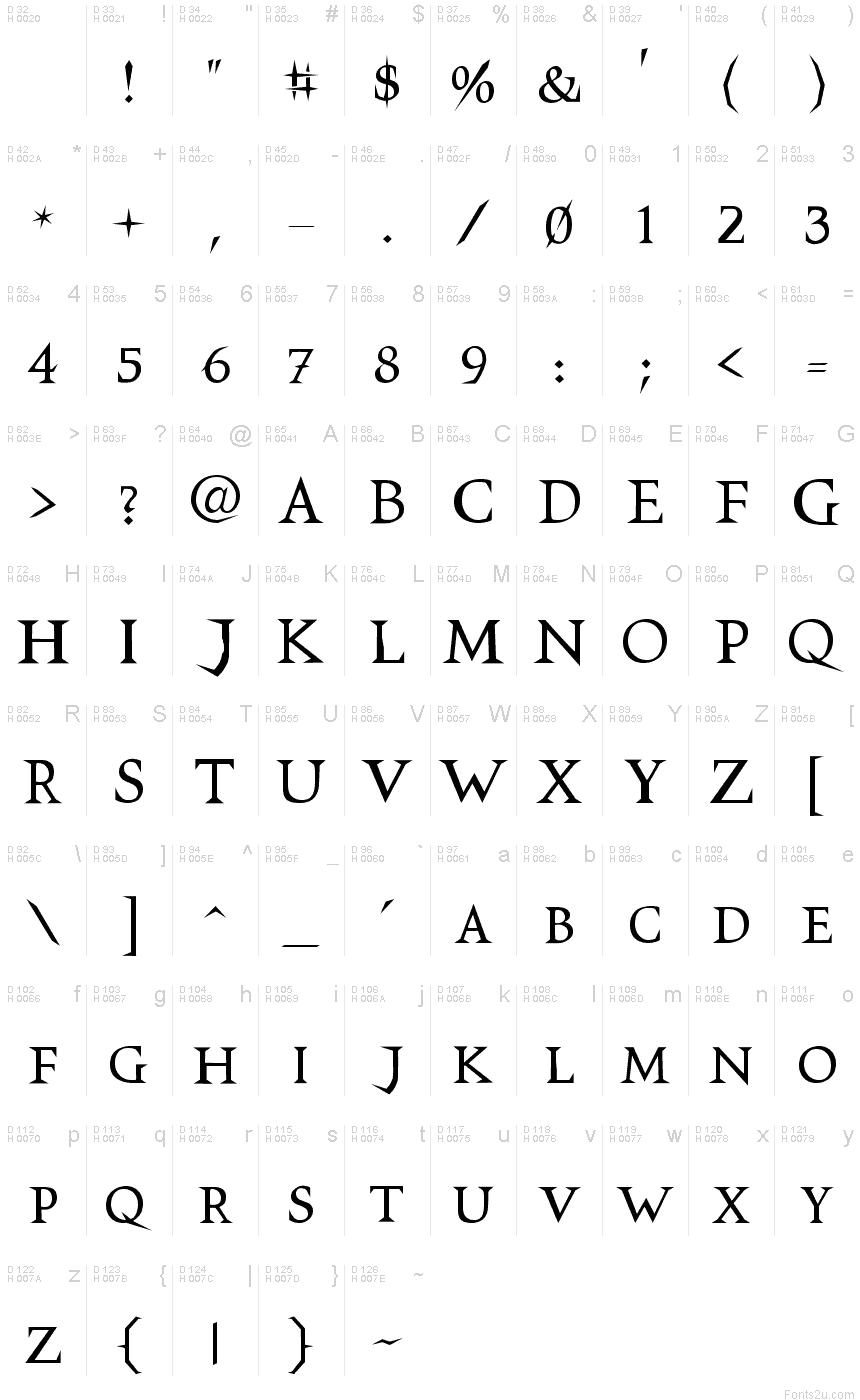
Podgląd czcionki VTCSwitchbladeRomance
VTC Switchblade Romance od V.T.C. Vigilante Typeface Corporation to darmowy krój displayowy w stylu retro z domieszką wiktoriańskiego melodramatu. Litery łączą wysokie, kontrastowe formy z ostrymi jak brzytwa szeryfami i gwałtownymi krzywiznami, dzięki czemu cały font sprawia wrażenie teatralnego, lekko drapieżnego i stworzonego z myślą o nagłówkach, a nie spokojnych tekstach.
Sprawdzi się na plakatach muzycznych, okładkach książek w stylu pulp, ulotkach klubowych, edytorialach modowych i nastrojowych planszach tytułowych, wszędzie tam, gdzie darmowy font ma natychmiast nadać klimat minionej epoki bez wpadania w karykaturę. Użyj go do krótkich nagłówków, logotypów lub inicjałów typu monogram, gdy chcesz, by cięta sylwetka i ostre detale grały główną rolę.